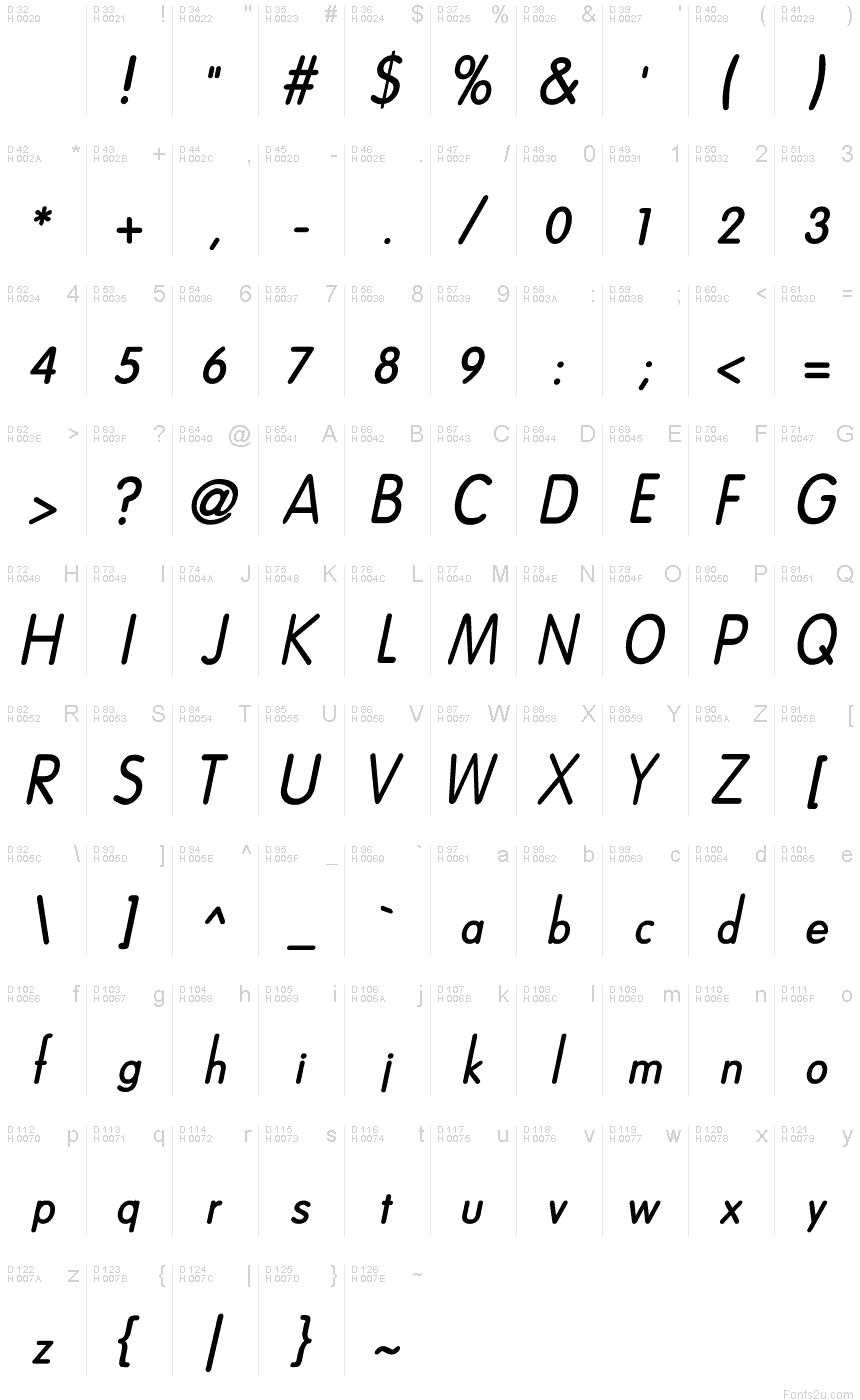
معاينة خط Dreamspeak Bold Italic
"Dreamspeak Bold Italic" من "Dreamfonts" هو خط مجاني عريض ومائل بلا زوائد (Sans Serif). تضفي منحنياته الانسيابية وضرباته المستديرة وميله الطفيف للأمام طابعاً ودوداً على النص، أشبه بخط يد مصقول ليناسب الشاشات. الحروف متقاربة دون أن تبدو مزدحمة، مما يمنح الكلمات حيوية وعفوية مع الحفاظ على وضوح تام حتى في الأحجام الصغيرة.
مع "Dreamspeak Bold Italic"، ستحصل على لمسة جاهزة للويب تتألق في اللافتات، وصور الواجهة الرئيسية، والشعارات، وقوائم التنقل، ورسوم وسائل التواصل الاجتماعي، وأزرار اتخاذ الإجراء (CTA). يضفي هذا الخط المجاني نبرة مريحة وحيوية تناسب العلامات التجارية العصرية والمواقع الشخصية المعبرة. جرب تنسيق "Dreamspeak" مع خط sans serif بسيط ومستقيم للنص الأساسي، واترك لـ "Dreamspeak" دوراً أكثر جرأة في الأحجام المتوسطة والكبيرة لتحقيق أقصى تأثير بصري.